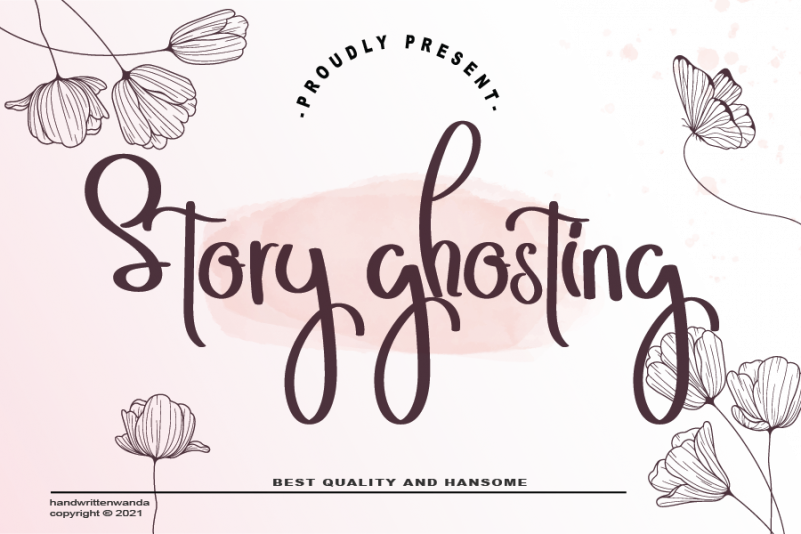
Story Ghosting Font – Download Grátis
A Fonte Story Ghosting é uma elegante tipografia script que transmite sofisticação e elegância sem esforço. Suas alternativas estilizadas e ligaturas meticulosamente cuidados criam um visual arrojado, perfeito para qualquer projeto. É ideal para designers em busca de uma fonte única que se destacará em qualquer layout ou design gráfico. A designer HandwrittenWanda criou esta font com precisão, resultando em linhas finas e espessuras bem equilibradas, garantindo a fluidez necessária para textos complexos e longos. Story Ghosting é uma escolha inteligente para quem procura um acabamento refinado para seu próximo projeto gráfico, seja ele corporativo ou pessoal.
Designer: handwrittenwanda